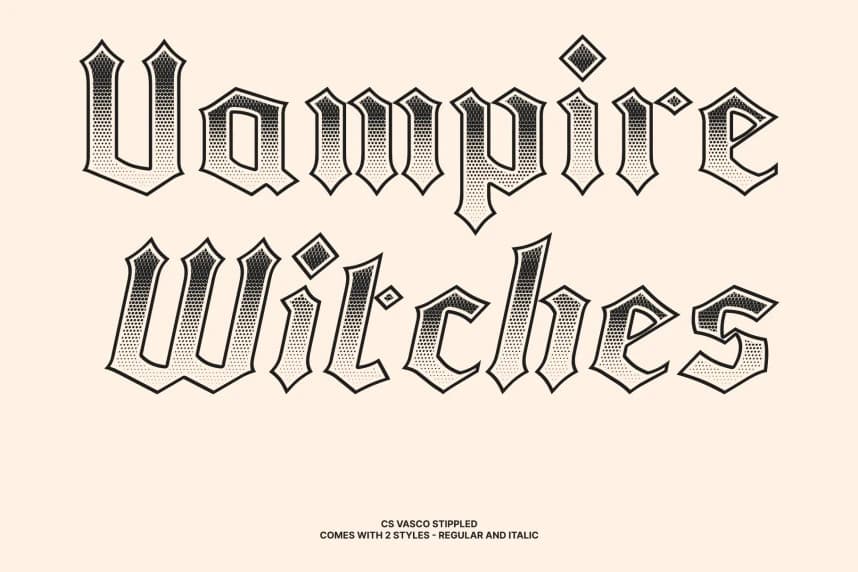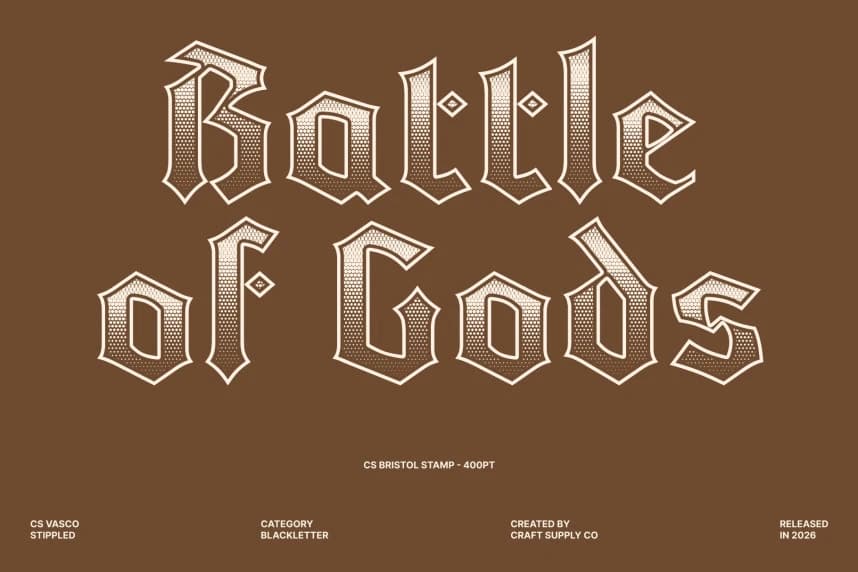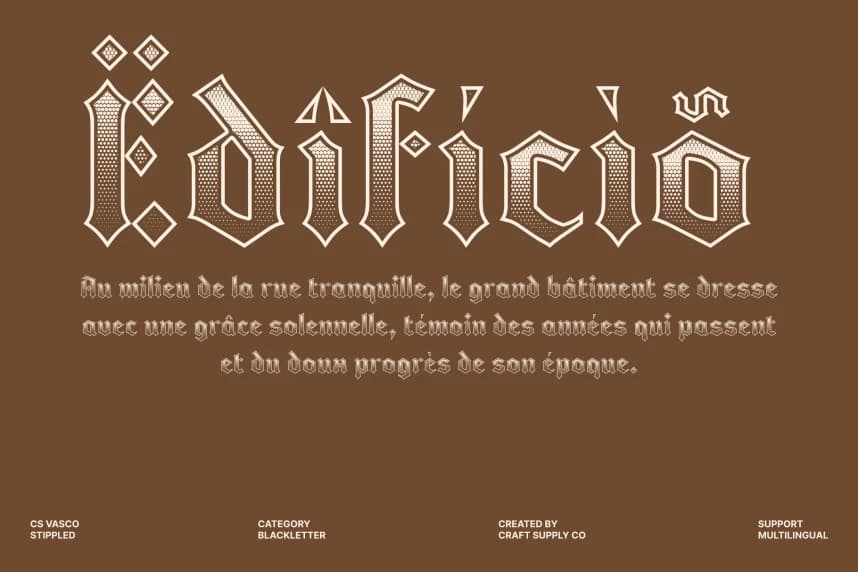
CS Vasco Stippled Yazı Tipi
CS Vasco Stippled Font – Blackletter Font ile zamansız dokulu gelenek, Classic Blackletter Style ile Stippled Depth. Bu, tarihî tipografinin zarafetini ve otoritesini yakalayan çarpıcı bir Blackletter display font'tur.
CS Vasco Stippled Font – Zamansız Dokulu Gelenek ile Blackletter Yazı Tipi – Stippled Derinlik ile Klasik Blackletter Tarzı. Bu, tarihsel tipografinin zarafeti ve otoritesini yakalayan çarpıcı bir Blackletter başlık yazı tipi.